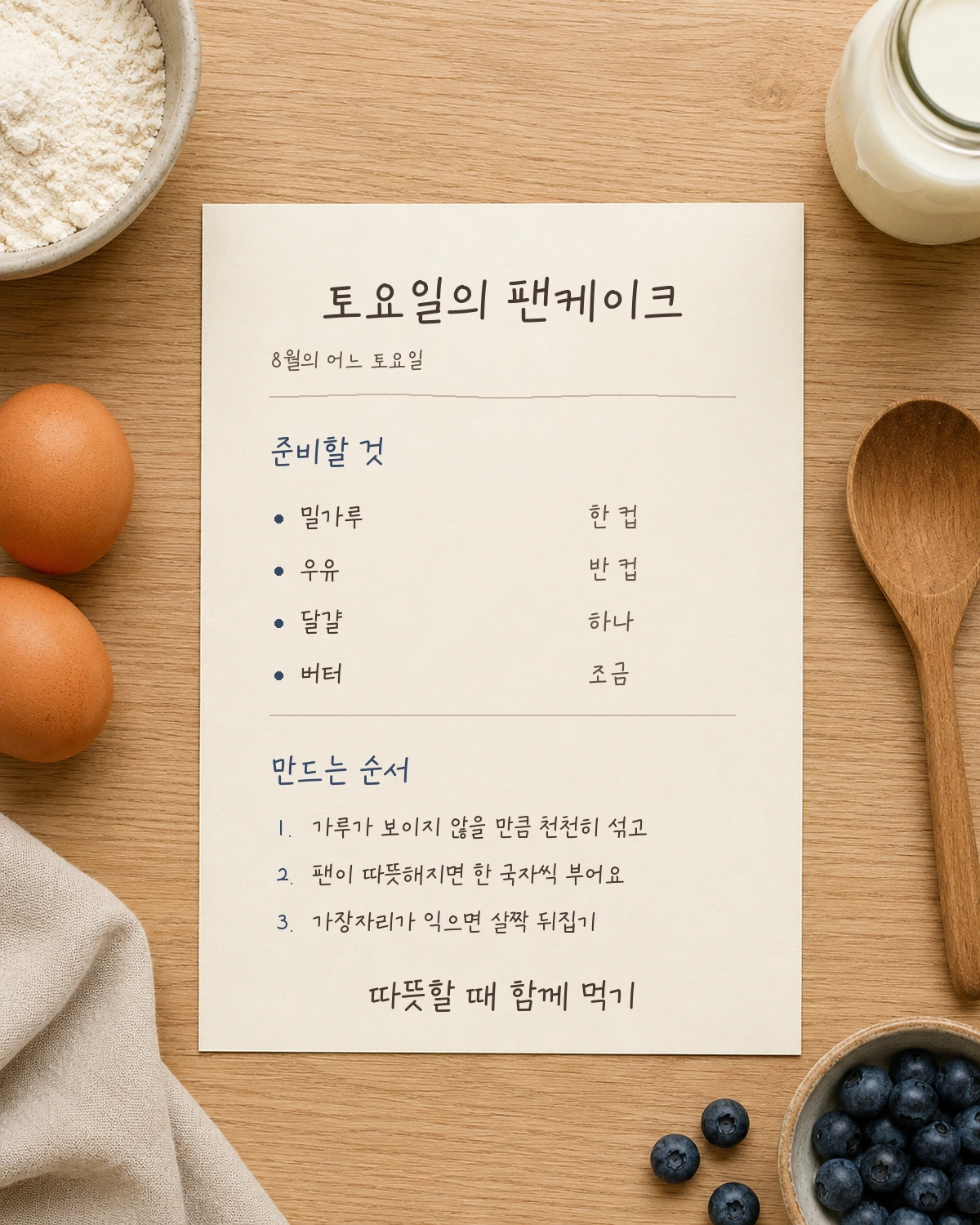
교보손글씨 이유빈체 — 교보문고에서 배포하는 무료 폰트입니다. 또박또박한 글자에 자연스러운 필압과 크기 변화를 담은 정갈한 손글씨체
교보문고가 해마다 여는 교보손글씨대회에서 2025년 제11회 일반 부문 으뜸상을 받은 이유빈 님의 손글씨를 서체로 옮긴 글꼴입니다. 그해 대회는 75,134명이 참가해 역대 최다를 기록했습니다.
수상자의 이야기가 남아 있습니다. 필사한 작품은 시 유월이었고, 시의 여유로운 분위기에 맞춰 여백이 많은 글씨체로 썼다는 것이 본인이 밝힌 비결이었습니다. 글쓰기 교본을 사서 하루 두세 시간씩 연습했다고도 했습니다.
배포처는 이 서체를 수수하고 정갈한 손글씨를 그대로 담았다고 설명하고, 보도자료는 길게 뻗은 균일한 획과 시원한 속공간, 사선으로 기울어진 가로획이 어우러져 단정하고 안정적인 인상을 낸다고 덧붙입니다. 현대 한글 11,172자를 모두 담아 어떤 글자를 넣어도 빠지지 않습니다. 무료로 쓸 수 있지만 폰트를 고치거나 다른 포맷으로 바꾸는 것, 다시 배포하는 것은 금지됩니다.